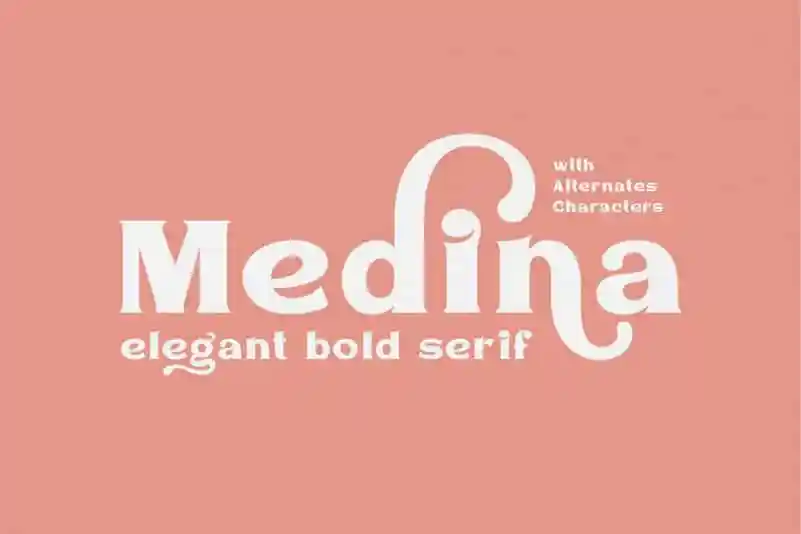
Medina Serif Font – Fonte Grátis
Medina Serif Font
Medina Serif é uma fonte serif com uma sensação equilibrada entre letras maiúsculas e minúsculas, apresentando uma aparência elegante e sofisticada. Este tipo de texto traz um toque de personalidade, perfeito para uso tanto em cabeçalhos quanto em textos mais longos. Viaction Type Co. é o responsável pela criação e partilha desta fonte, que oferece um visual elegante e arredondado que se adequa especialmente a trabalhos de temas elegantes ou vintage. Perfeita tanto para anúncios elaborados quanto para descrições detalhadas em um site ou aplicativo.